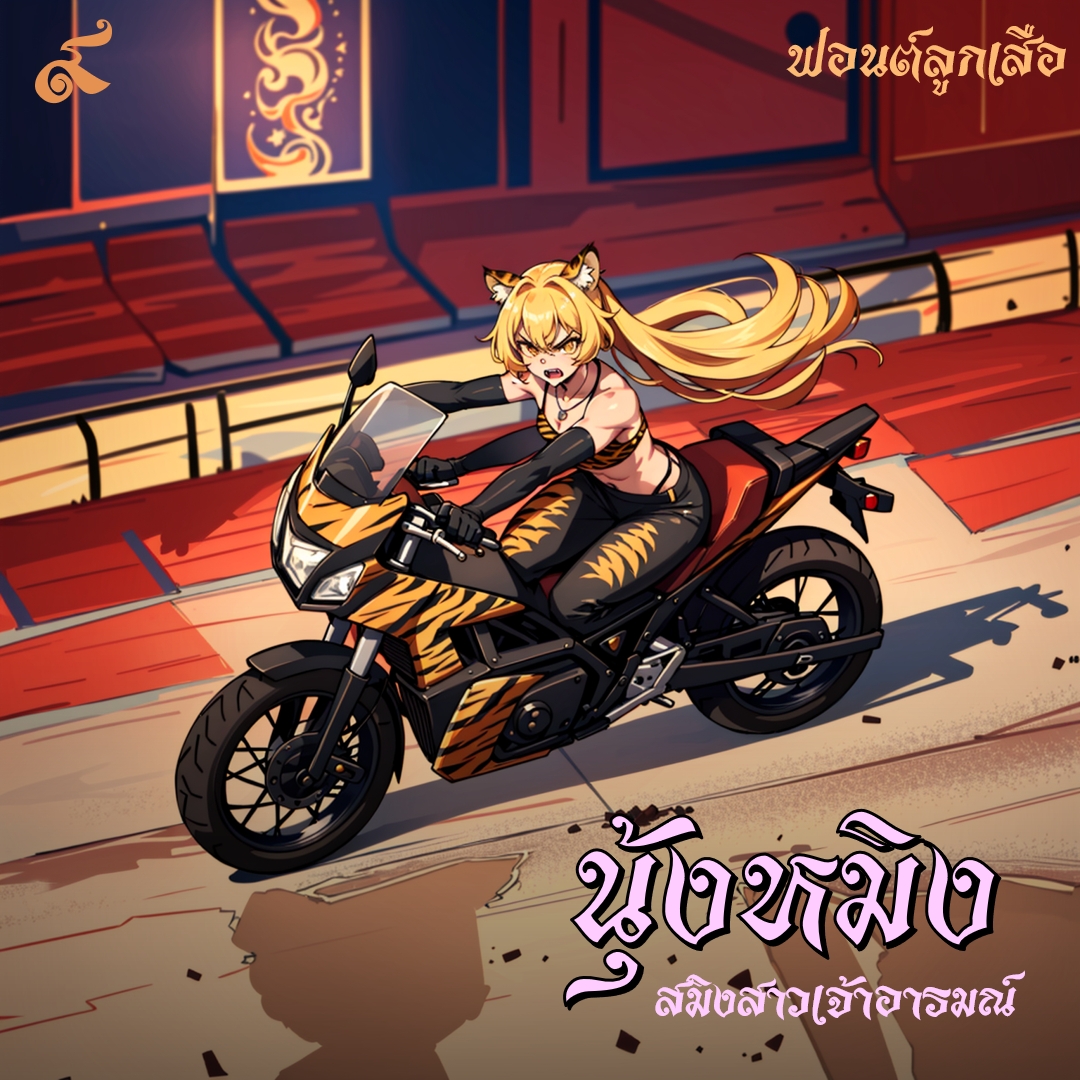
ฟอนต์ ลูกเสือ
ฟอนต์ลูกเสือ ฟอนต์ประกอบภาพที่เล่าเรื่องราวของพี่น้องสองเสือที่เข้ามาผจญภัยในเมืองใหญ่
นุ้งหมิง เป็นเสือสมิง จริงๆน้องไม่ได้ขี้วีน แค่ขี้เก็ก พยามยาม keep look ทำหน้าดุอยู่ตลอด
ไปไหนมาไหนกับพี่ชาย
เพ่ตุ๊ก เป็นเสือที่สามารถแปลงร่างเป็นยานยนต์ได้ทุกอย่าง แต่ชอบมากคือ รถตุ๊ก
มีทั้งแบบ ครึ่งตัว
เต็มตัว
ภาพตัวอย่าง การผจญเมืองใหญ่ของ 2 พี่น้อง
อ้าว! เกือบลืมว่าทำฟอนต์  55.. สรุป ฟอนต์นี้เหมาะพาดหัวเช่นเคย
ฟอนต์ลูกเสือ ใช้ประกอบการเล่าเรื่อง การผจญภัยในเมืองใหญ่ ของพี่น้องสองเสือ ..เดี๋ยวๆ! เอาใหม่ ฟอนต์นี้ต้นทางจากปกหนังสือธรรมะใช้พาดหัวเช่นเคย
ที่จริงฟอนต์มันไทยมากเลยนะครับบบ